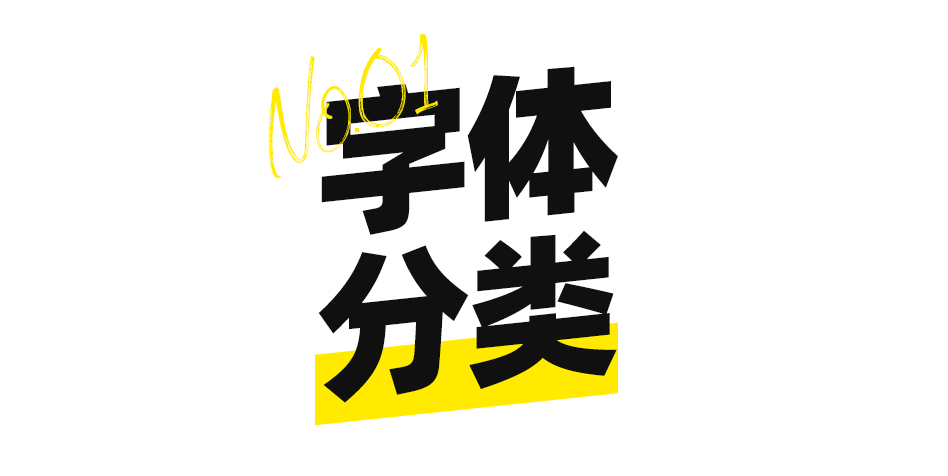
那啥~干货教程又来了~
我们都知道,平面设计最重要的载体是文字。它可以说是设计的传话筒,设计师通过文字传达信息,同时又将文字作设计的素材,进一步赋予文字更深刻、更丰富的内涵,而字体在这个过程中扮演了重要的角色。
因此,了解字体,学会怎么使用字体,是一个设计师最基本的功底。对于非设计行业的人来说,了解字体的特性,在PPT或者WORD文档中用对字体,也是审美能力的体现。
今天这篇文章,我就带大家从字体的分类,到不同字体适用什么场景,再到排版中的字体使用规则,全方位提升大家对于字体的认识。
OK,废话少说,干货走起。
选择字体最重要的标准是什么?
两个字:气质。
没错,主要看气质。
先来个案例大家感受一下不同字体的气质区别有多大。
下面这张文艺风的广告图很漂亮对吧?但是字体用得有点粗重呆板,明显和画面的文艺风有点格格不入。
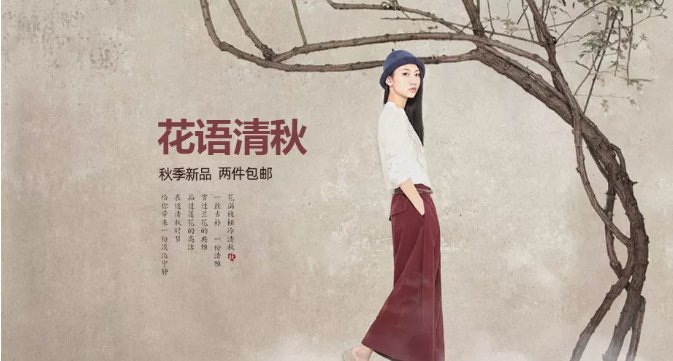
我将字体换成轻盈典雅的宋体后,然后在排版上稍加变化,是不是整个气质就完全不一样了?
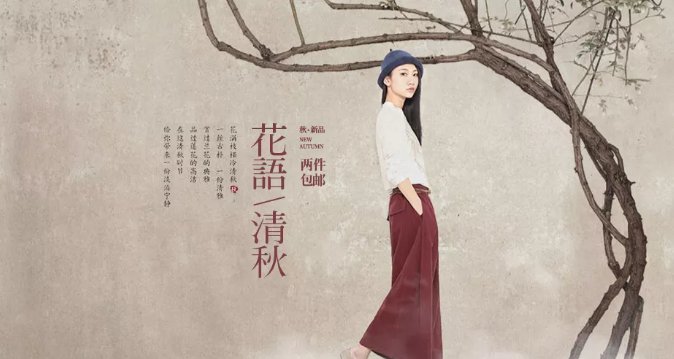
所以字体、排版、图片风格这三者是相辅相成的,对排版来说,选对合适的字体,是第一步。
那么问题来了,什么是合适的字体?怎么知道什么画面配什么样字体?
OK,要弄清楚每种字体的性格气质,我们首先需要对所有的字体有个大概的分类。
中文字体:
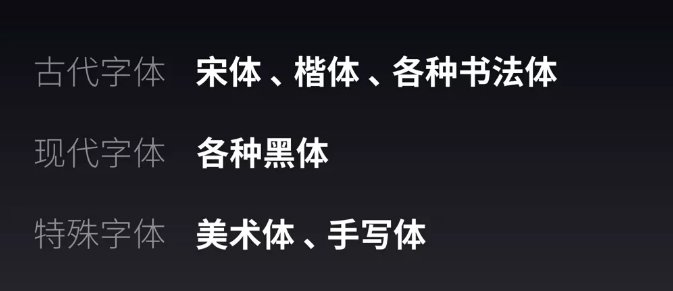
英文字体:
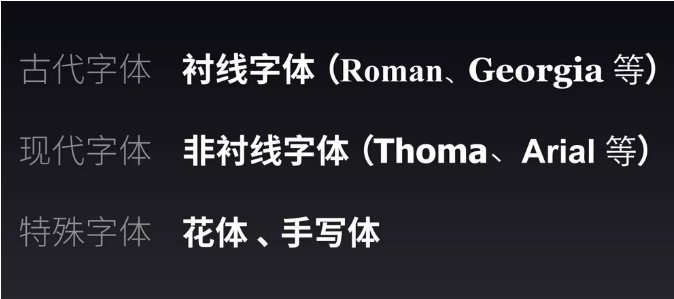
当然,这只是一个比较大的分类方法,大家只需要有个大概的印象即可。
在实际的应用中,我们对字体有更多的分类维度,为了让大家有一个更直观的印象,我制作了一张四象限图,大家参照这个图,看看相应的字体可以放在哪个位置,这样就对每个字体用在什么场合,就大概心里有谱了。
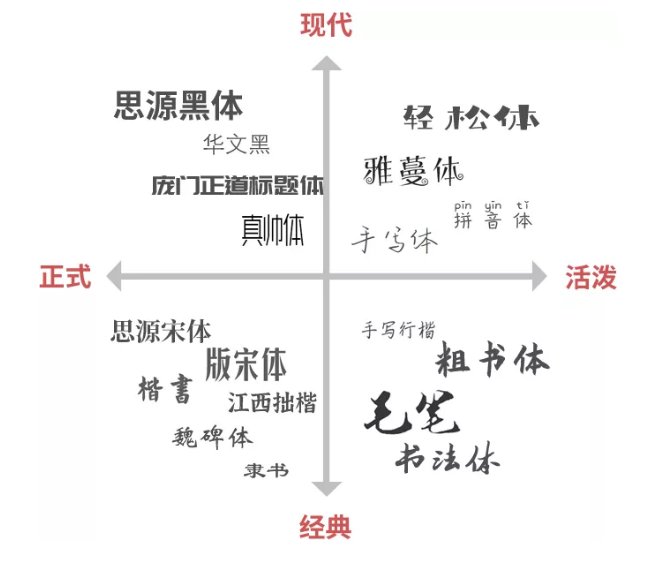
虽然字体的数量有无数种,但是其实每种字体都可以归到上面的座标图中,大家只要记住这个分类方法,时间久了一眼就能知道某个字体的大概特征,可以怎么用。
说完字体的分类方法,接下来看看在实际的工作中,到底是按什么规则来选择合适的字体。